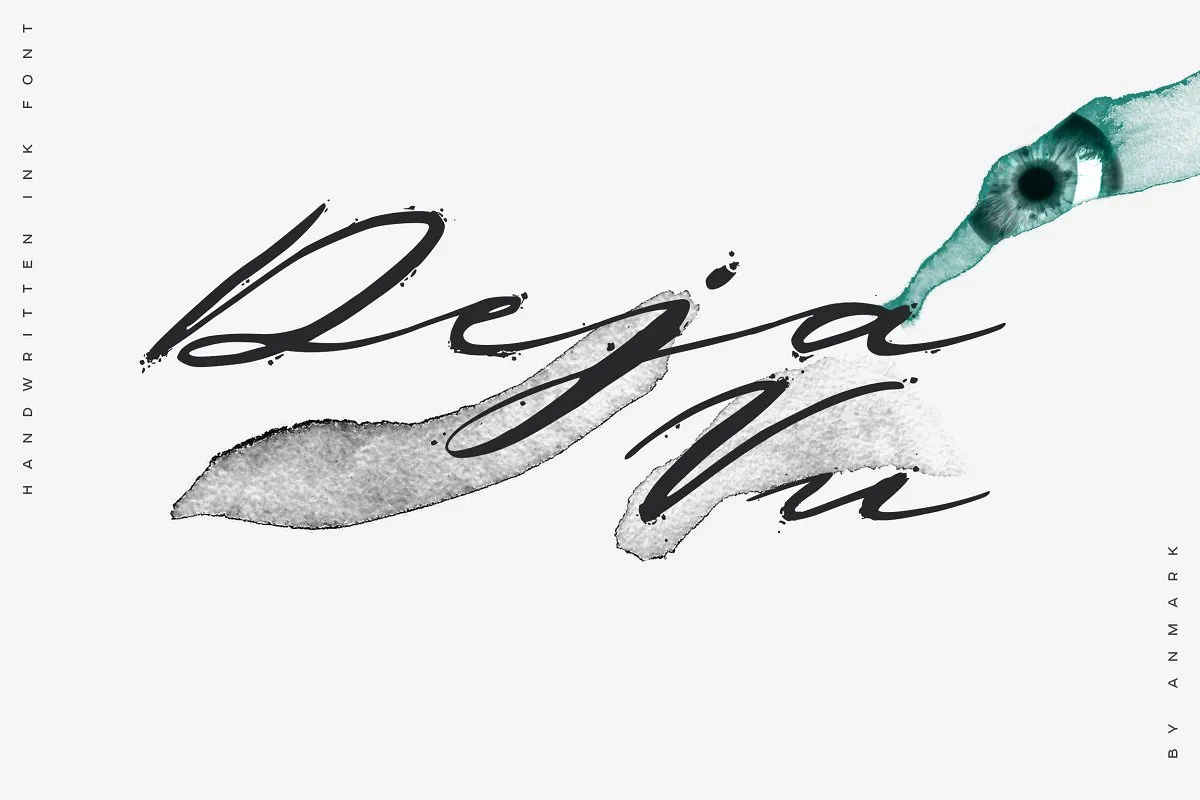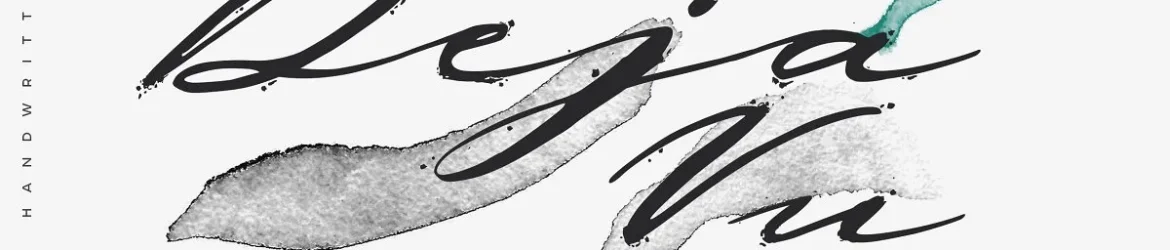
Deja Vu Handwritten Ink Font – Download Grátis
Introduzimos a fonte Deja Vu Font. Ela foi criada pelo designer anmark, é uma fonte premium disponível no Creativemarket, mas está agora gratuita para download hoje. A fonte Deja Vu Handwritten Ink é um tipo de efeito esfumaçado em estilo escrita. Cada letra maiúscula e minúscula tem borrões únicos de tinta. Este design decorativo se destaca perfeitamente para logotipos, projetos de marca, tatuagens, embalagens, mídias sociais, assinaturas e cabeçalhos e muito mais. Descubra por que essa fonte é tão versátil e adicione o toque final a seu projeto visual com Deja Vu Handwritten Ink Font.